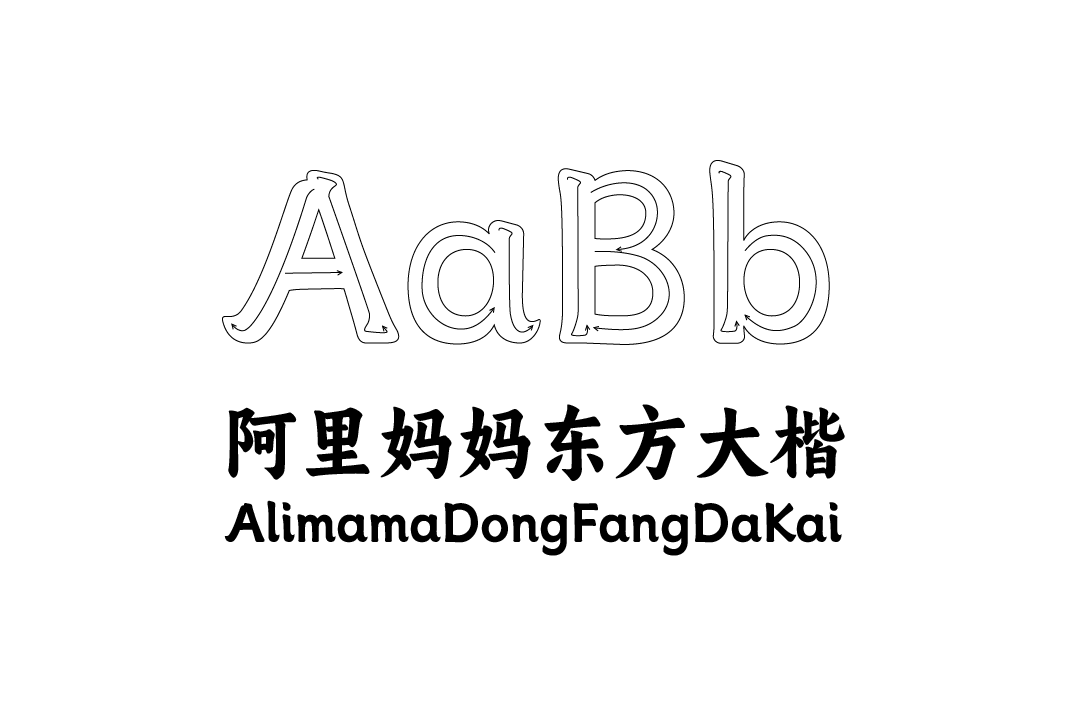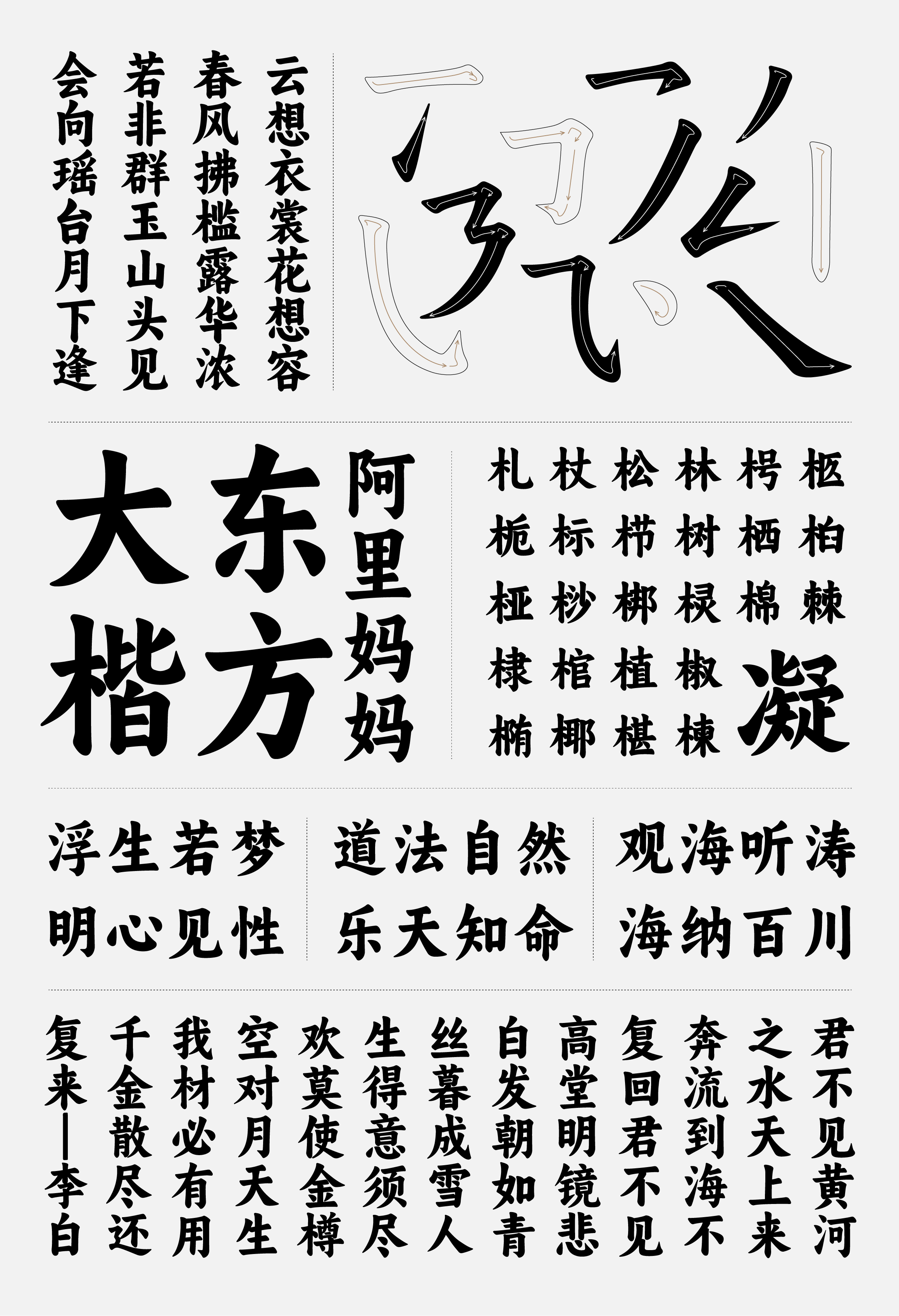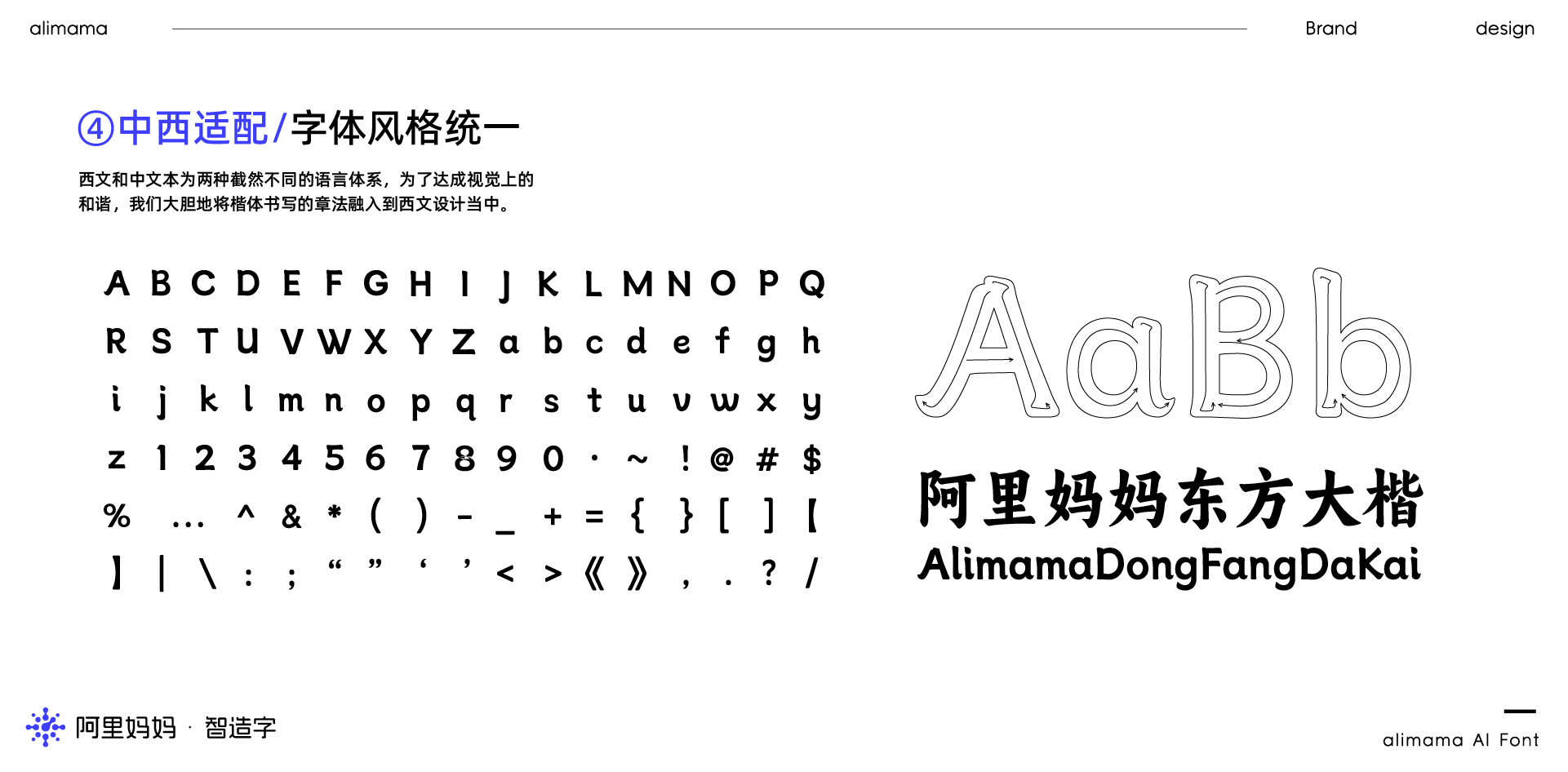
阿里妈妈东方大楷是阿里妈妈技术团队运用AI(人工智能技术)结合颜真卿的多宝塔碑算法生成的一款中文颜体字库,并声明可免费商用。
阿里妈妈东方大楷字体拥有颜体的丰腴厚重之感,在笔画的描摹上做到了传统书法的收放起伏,规范了骨架、笔画,还原了书法中的落笔、转笔、藏锋、护尾等书写韵味,使整体更饱满、圆融、浑厚。
阿里妈妈东方大楷为中文简体字库,收纳的中文字符包括但不限于GB2312,共计6763个汉字;英文大小写(含全角、半角、合体字等)共105个;常用标点符号共175个,总计7043个字符。
Ps:《多宝塔碑》全称《大唐西京千福寺多宝塔感应碑》,天宝十一年(752)四月廿日建,岑勋撰文,颜真卿书丹,徐浩题额,史华刻字,现藏西安碑林。是颜真卿早期的代表作品,为后人初学书法的极佳范本。但是,多宝塔碑并没有形成颜真卿宽博雄浑的风格特点。此碑用笔笔笔藏锋、笔笔回锋,结构疏密匀称,风格严谨庄重。临习多宝塔碑应注意用笔的提按转折、结构的内紧外松和上紧下松,细心观察,仔细研究其用笔特点及结构规律,学好此碑只是时间的问题。(来源网络)